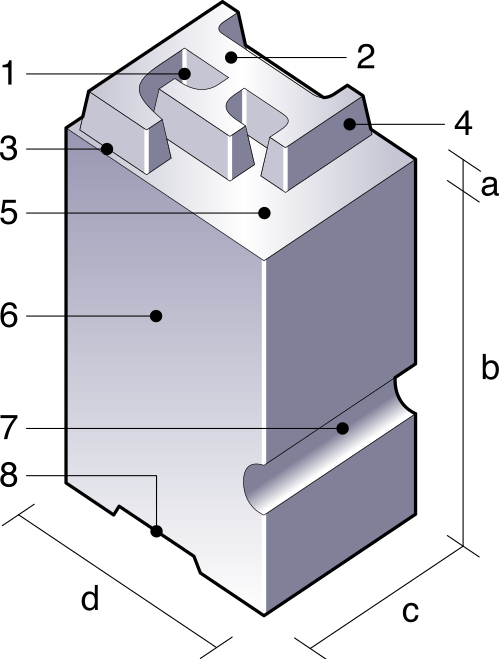
Geviert einer Schrift ermitteln, aber wie ?
ich habe mich ein bischen im Forum "eingelesen" und dabei bin ich über das Geviert gestolpert.
Ich gehe mal davon aus, das diese Größenangabe bei jeder Schrift anders sein sollte?
Bei Cleverprinting fand ich von Günter Schuler folgende Aussage:
"Das Geviert ist eine Konstruktionsgröße – ein virtuelles Quadrat, dessen Höhe von der Unterkante des kleinen g bis zum oberen Ende der Punkte auf dem großen Ä reicht. Die genauen Abmessungen hängen von der verwendeten Schriftgröße ab. Bei 72 pt Schriftgröße ist das zugrundeliegende Geviert 72 pt breit und 72 pt hoch."
Bei einem früheren Thema (Leerzeichen in Unicode) habe ich dann gefunden, daß die Schriften selbst die Größe beinhalten:
U+2001/U+2002 Geviert-Leerzeichen
U+2000/U+2002 Halbgeviert-Leerzeichen
usw.
Deshalb habe ich mal dieses in Word 2010 für die Schriften Arial, Calibri, Cambria und Times New Roman ausprobiert:
jeweils die Schriftgröße auf 240 formatiert, die Breite der Zeichen ausgemessen und anschließend auf die Standardgröße von 12 umgerechnet.
Beim Auswerten der Ergebnisse mußte ich aber feststellen, daß die gemessenen Größen für Geviert und Halbgeviert bei den 4 Schriften gleich groß sind!!??
Wenn ich die Methode von G. Schuler nehme, erhalte ich für jede Schrift andere Werte.
Bei anderen Schriften wollte ich das auch noch mit den Unicode-Zahlen ausprobieren, aber bei viele Schriften sind die o.g. Unicode nicht belegt.
Was ist richtig ?
Bei 72 pt Schriftgröße ist das zugrundeliegende Geviert 72 pt breit und 72 pt hoch."
Das sollte eigentlich alles beantworten. Das Geviert ist ein Quadrat mit den Seitenlängen der Schriftgröße. Wenn die Schriftgröße 12 Punkt ist, dann ist das Geviert 12 Punkt, egal ob in Arial oder Calibri. Wie viel Raum die Buchstaben auf diesem Geviert einnehmen, kann jedoch von Schrift zu Schrift unterschiedlich sein.
Das Geviert ist eine Konstruktionsgröße – ein virtuelles Quadrat, dessen Höhe von der Unterkante des kleinen g bis zum oberen Ende der Punkte auf dem großen Ä reicht.
ist natürlich in gewisser Weise Blödsinn - zwischen der Unterkante des kleinen G und der Unterkante des (Konstruktions-)Gevierts (was dem Bleisatz-Kegel vergleichbar wäre) und ebenso über dem Ä kann durchaus noch Luft sein. Sonst wären die unterschiedlichen Fonts bei gleicher Punktgröße ja tatsächlich "gleicher" in der Größe. Das Geviertzeichen ist bzw. sollte dann in diesem Fall ungefähr so sein, wie Schuler sagt - also kleiner als das Konstruktionsgeviert bzw. der Kegel.
Im Bleisatz ist man da sparsamer gewesen und hat den Kegel, der hier auch gleichzeitig das Geviert bildete, in der Regel voll ausgenutzt. Deshalb kann man sich unter einer 12p Bleisatzschrift auch eine bestimme Größe vorstellen (von ein paar exotischen (meist Schreib-)schriften mal abgesehen. Bei digitalen Fonts hingegen kann 11p durchaus noch lesbar sein, muss es aber nicht ...
ist natürlich Blödsinn …
Das ist einfach als bewusst faustregelartige Erklärung gemeint – damit man sich unter diesem Maß als Laie überhaupt irgendetwas vorstellen kann. Blödsinn ist es nicht.
Wenn man das Zitat nicht unfairerweise abschneidet, heißt es ja dann auch »Die genauen Abmessungen hängen von der verwendeten Schriftgröße ab. Bei 72 pt Schriftgröße ist das zugrundeliegende Geviert 72 pt breit und 72 pt hoch.«
Und das stimmt ja.
(Ob es glücklich erklärt ist, sei jetzt mal dahingestellt.)
Bei 72 pt Schriftgröße ist das zugrundeliegende Geviert 72 pt breit und 72 pt hoch.
stimmt dann aber eben bei Schulers Faustregel nicht mehr, weil man ja nie weiß, wie großzügig der digitale Schriftschöpfer oben und unten noch Raum gelassen hat (bzw. Raum nicht genutzt hat) auf seinem "Kegel". Weshalb dann eine auf 72p eingestellte Schrift möglicherweise gar nicht wirklich 72p hoch ist und deshalb das Geviert auch nicht 72p im Quadrat sein sollte.
Deshalb hat der Anfragende ja auch unterschiedliche Werte ermittelt.
Gibt es eigentlich einen einsehbaren vernünftigen Grund warum anscheinend recht viele Digitalfontsschöpfer ihr Konstruktionsquadrat nicht voll ausnutzen und somit dann eher "zu kleine" Schriftgrade erzielen? Ich fände es viel praktischer, wenn ich wüßte 12p sind 12p. Und nicht noch Spezialkenntnis darüber bräuchte, wie die jeweilige Schrift denn so ausfällt ... Es wäre dann beispielsweise viel einfacher, am Telefon über Schriftgrößen zu reden ...
Das war im Bleisatz wirklich einfacher ... da waren 12p fast immer 12p ... aufm Kegel, der das Geviert ergab ...
Die Faustregel sagt doch nur, dass das Geviert (also der Kegel) ungefähr die Unterlängen und die Versal-Akzente gerade so einschließt. Das trifft auf die meisten Schriften zu und ist daher als Aussage an Otto Normal okay.
Das Missverständnis entstand hier beim Threadersteller wohl wieder auch daher, dass man eben Schriftgrößen (und damit auch Geviert) überhaupt nicht am Druckbild ablesen kann.
Ich hatte dieses ja nur aufgeführt, weil hier gesagt wurde, dass in der Regel das Maß von Oberlänge der Versalien mit "normalen" Akzenten oder, so diese höher sind die Oberlängen der gemeinen bis zur maximalen Unterlänge der gemeinen oft kleiner als die angegebene Schriftgröße und damit dem Geviert ist - hier ist dieses Maß eben größer. Und so sind wir eben bei einem Satz, den ich eigentlch aus einer ganz anderen Szene kenne: "Alles geht, nichts muss"